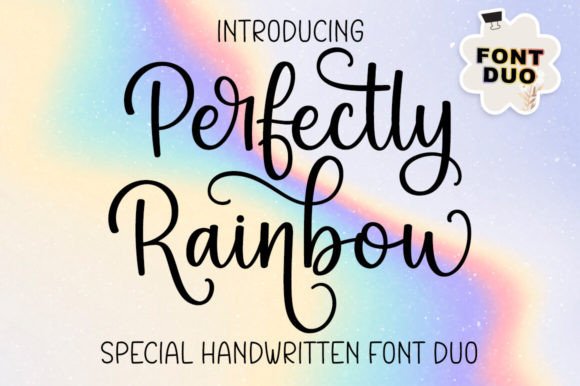
Perfectly Rainbow 字體免費下載
今日的免費字體是 Perfectly Rainbow,由設計師 Graphix Line Studio 創作,於 2023 年 9 月正式上架,目前已累積 3148 人收藏最愛、27 則評價全數 5 星滿分。這款字體共包含兩款互補字型,設計風格活潑又不失優雅,適合用在兒童活動設計。
字體已通過 PUA 編碼 (PUA Encoded),這代表你可以透過字符對照表輕鬆存取所有額外的花體字符、飾字和連字 (Swashes & Ligatures),即使使用 Cricut、Silhouette 等切割機軟體也完全相容。